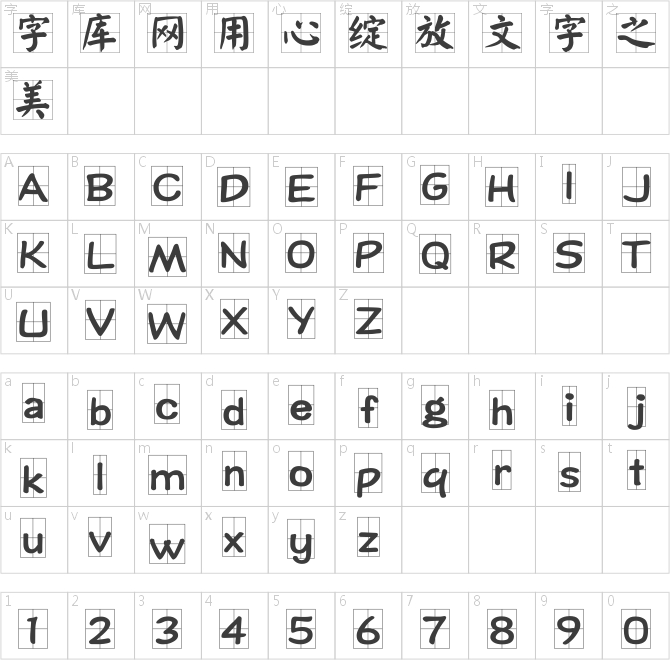
字體名稱: 文鼎習字體簡繁
本人將「文鼎大顏楷big5」合并入「文鼎習字體」并將所添加的漢字加了「文鼎習字體」的田字格形成了「文鼎習字體簡繁」。原生兼容新版win10。
文鼎習字體簡繁字體字庫是一款讓人賞心悅目、百看不厭的中文字體,適合各類廣告和產品包裝設計應用,字體大小17.94MB,格式為ttf字體,上傳用戶是伊寧,作者/版權方為文鼎字庫